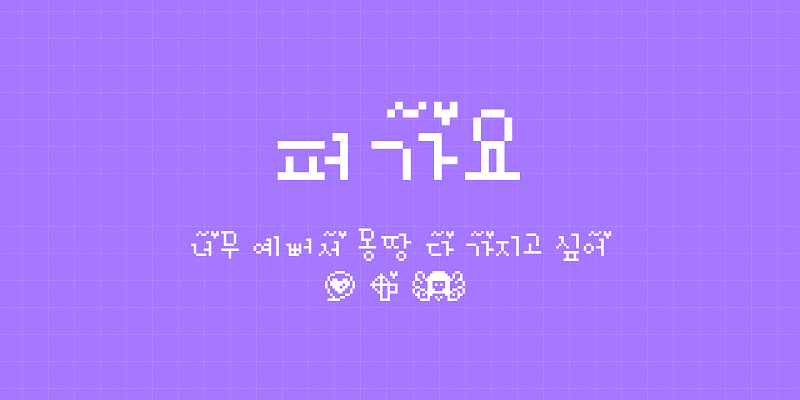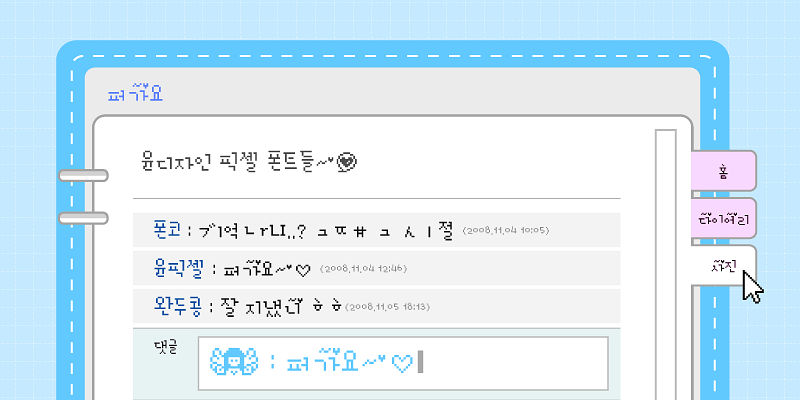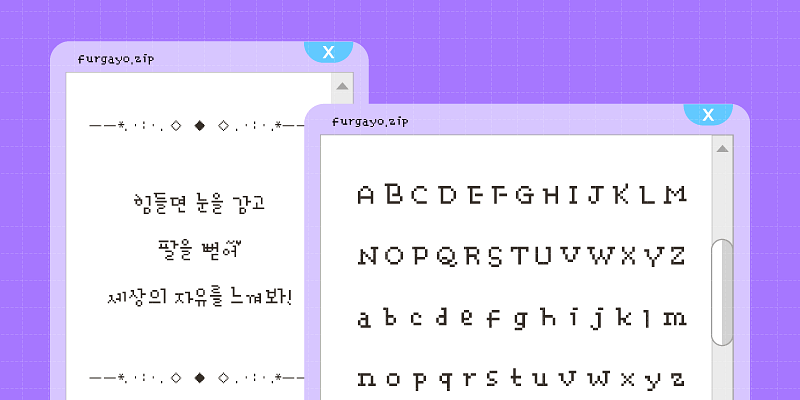
Créée par Yoondesign Group, cette police pixel a été modernisée et vectorisée à partir des anciennes écritures pixel traditionnelles pour s’adapter aux sensibilités esthétiques contemporaines.
Furgayo se caractérise par les cœurs ondulés qui viennent orner certaines lettres telles que 가, 니, 어 ou 시. Elle incarne le charme et la douceur typiques des commentaires nostalgiques tels que « Scrapping~♥ », que l’on retrouvait souvent sur les albums personnels de scrapbooking photo en ligne. Prenant en charge 11 172 caractères hangeul, elle garantit une représentation exhaustive de chaque lettre coréenne.